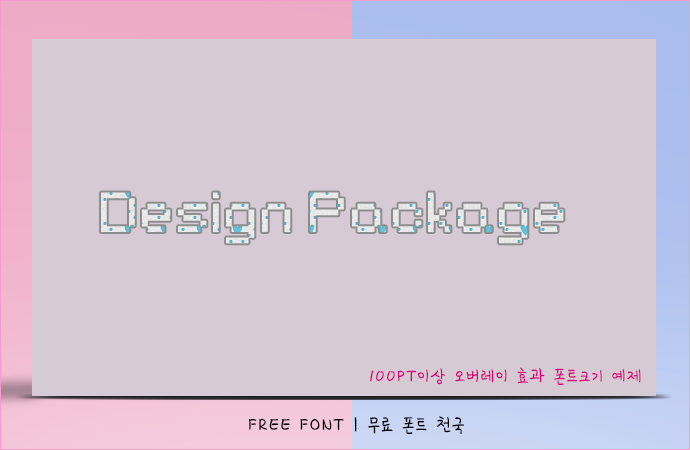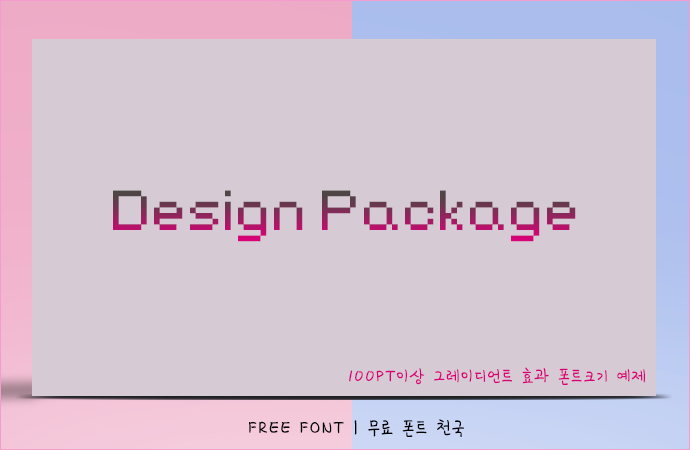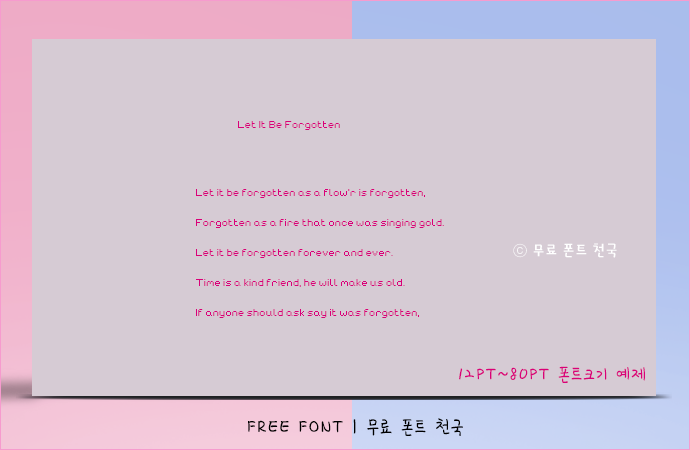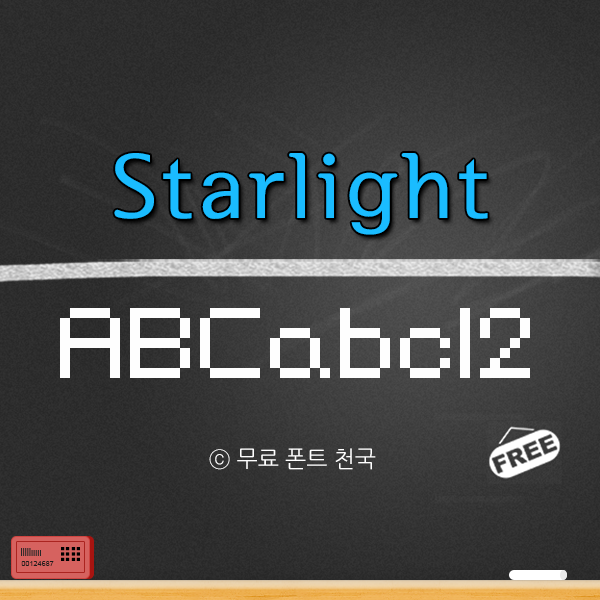
작은 스타일의 폰트가 필요할 때 Starlight 영문 폰트
Starlight 폰트 정보
9PT 크기의 작은 폰트에 가장 최적화된 미니멀한 서체 Starlight 폰트입니다. 8~9pt 크기 이상으로 폰트 크기를 적용할 경우 아래 예제 처럼 도트 스타일의 폰트로 변경되니 폰트에서 지원하는 크기 그대로 사용을 원하시는 분들은 9pt 이하의 크기에서 사용하시길 바랍니다. Starlight 폰트는 누구나 자유롭게 사용 가능한 무로 서체입니다.
Starlight 폰트 # 미리보기
Starlight 폰트, 9PT 크기로 적용한 효과
Starlight 폰트, 100PT 크기 이상으로 작업한 오버레이 효과
Starlight 폰트, 100PT 크기 이상으로 작업한 그레이언트 효과